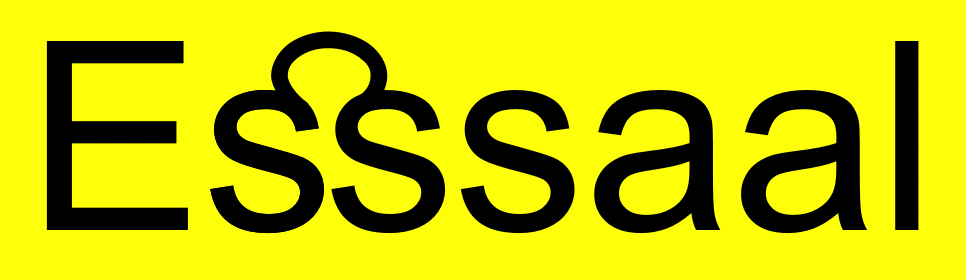
Brauchen wir eine ss Ligatur?
Bei Typedrawers wird gerade diskutiert, ob es Sinn macht, eine ſß Ligatur einzuführen, die die drei sss bei Worten wie "Esssaal" ersetzen könnte. Ich habe mich da eingemischt, um klarzustellen, daß ein Eszett hier nicht zur Wahl steht, denn Esßaal gibt's nicht, und "Eßsaal" auch nicht.  Im Fraktursatz würde man Eſſsaal schreiben. Langes s ist ja nicht mehr im Gebrauch, und so schlug ich eine ss-Ligatur vor.
Erst danach kam ich darauf, meine Meinung nachzuprüfen. Siehe da, "Eßsaal" gibt es sehr wohl. Meine Frage an Euch jetzt: ist die Verwendung des Eszetts hier nur Usus, aber streng gesehen nicht richtig? Oder bin ich völlig auf dem Holzweg? (Bitte bedenken, daß meine Deutschkenntnisse auf dem Stand von 1990 eingefroren sind.)
Orthographisch korrekt ist heute Esssaal. Da im Deutschen grundsätzlich keine Ligaturen über Fugengrenzen gesetzt werden, kann hier auch keine sss-Ligatur angewandt werden.
(Wenn ich das Wort in Fraktur setzen müsste, würde ich entweder Eßſaal (Rechtschreibung von 1901) oder Eſsſaal schreiben.)
Yeah, Rechtschreibreform!
Da das Eszett einen Silbenschluß bildet und niemals eine Silbe öffnen kann, stellt sich für mich da auch nicht die Frage nach einer Ligatur.
Mmm, ich bin da wohl zu phonetisch gewesen, Straße wird mit einer mit ß-beginnenden Silbe getrennt: Stra-ße. Wobei ich lautsprachlich eher eine Doppelkonsonanz höre: Stras-se. Kein Wunder, dass es eines der schwierigen Wörter beim Duden ist.
German has recently undergone an orthographical revision which leads to the sequence sss often being present in words, which leads to awkwardness.
Surely the obvious solution is:
ſſs ſß
Weiß nicht, wie ernst das überhaupt gemeint war, aber es ist so oder so eine aus Unwissenheit geborene Idee. Es fehlte das Wissen, wo die verschiedenen Formen überhaupt historisch stehen können (was die gezeigten Formen komplett unmöglich macht), wie Ligaturen im Deutschen gesetzt werden und was diese Zeichen heute als sinntragende Einheiten bedeuten. Es sind halt keine grafischen Varianten, die man nach optisch-typografischen Erwägungen verteilen könnte.
Keine Frage, das habe ich auch dort kommentiert.
Ich hatte eher an so etwas gedacht:
Ja, das würde funktionieren, wenn es sich grundsätzlich so durchsetzen würde. Solange es die Ausnahme ist, stört es wohl eher als es nützt. Alternativ könnte auch das dritte s markiert werden. So wie es einige Sprachen ja mit dem Trema machen. Das ‘ë’ im Niederländischen ‘Ideeën’ steht nicht für einen anderen Laut, sondern sagt ‘neue Silbe ab hier’. Entsprechend könnte man Essšaal oder ähnliches schreiben.
(Nur als rein akademische Auseinandersetzung. Ich schlage nichts dergleichen wirklich ernsthaft vor.)
Solche Lösungen können meiner Meinung nach nur im Display-Satz funktionieren. Im Fließtext würde ich darüber jedes Mal heftig stolpern, da es ein unerwartetes Zeichen ist.
In der Diskussion wird behauptet Eſßall und Kurzschluſßtrombegrenzungsdrosseln seien für deutsche Leser verständlich. Klar kommt man irgendwie drauf, was gemeint sein soll. Aber mal ehrlich: Wer – außer Typografen, Historikern und sonst mit alten Schriftstücken befassten Leuten – kann heute noch etwas mit einem Lang-ſ anfangen?* Und wer würde je darauf kommen, ein ß aufzuspalten in das letzte s des einen Wortteils und in das erste s des nächsten Wortteils? Absurd! Hoffentlich entstehen aus dieser Diskussion keine irrigen Vorstellungen, die in neue Schriftentwürfe einfließen.
* Als ich mit der Buber-Rosenzweig-Bibel zu tun hatte, stieß ich in dem beigefügten Heftchen zur Entstehung der Übersetzung auf das Lang-ſ. Der Text war nicht etwa in Fraktur, sondern aus einer Antiqua gesetzt. Schnell war mir klar, dass ein s gemeint sein muss. Aber ich habe lange nicht verstanden, was es mit diesem f-ähnlichen Spazierstock im Text auf sich hat.
Naja, das ſ ist ja sicher nicht grundlos verschwunden. Ich baue es trotzdem in alle meine Schriften ein, und habe mir auch die Mühe gemacht, das "historical forms" feature so zu erweitern, daß ſ nur am Wortanfang auftritt. Um im deutschen Satz Wortfugen zu erkennen, und da das richtige s einzusetzen, dafür ist allerdings noch kein Kraut gewachsen.
noch kein Kraut gewachsen
Es gibt Ligaturix und MacFrakturix. Ob die Programme was taugen, kann ich nicht beurteilen. Ich habe sie noch nie eingesetzt. Die Frakturschriften von Delbanco und Helzel haben eine Lang-ſ-Automatik (ob alle, weiß ich nicht). Ich schalte die Funktion immer aus. Ich setze das Lang-ſ und das Rund-s lieber manuell.
PS: Programmmnemotechniker
Die einzige davon, die mir in freier Wildbahn begegnet ist, ist die Sauerstoffflasche.
Und nein, geärgert nicht, aber sie hat mich schon etwas angefremdelt. ;-)
Natürlich ist es konstruiert. Ich habe lange gesucht, um eine halbwegs glaubhafte Kombination zu finden, deren erster Teil auf Doppel-m endet und deren zweiter Teil mit m und einem weiteren Konsonanten beginnt. (Ich wollte Bernd ein bisschen sticheln. Manchmal juckt der Hafer. War also gar nicht böse gemeint.)